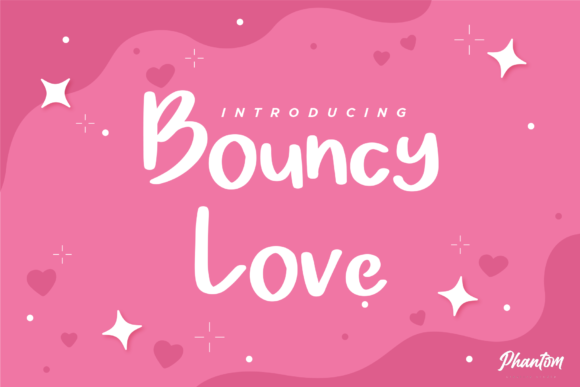
Bouncy Love
Bouncy Loveのような高品質の素材をお探しの場合、このプレミアムパッケージはクリエイティブなプロジェクトに素晴らしい選択です。
POD(オンデマンド印刷)製品、結婚式の招待状、またはソーシャルメディアのグラフィックを作成している場合でも、Bouncy Loveは理想的です。